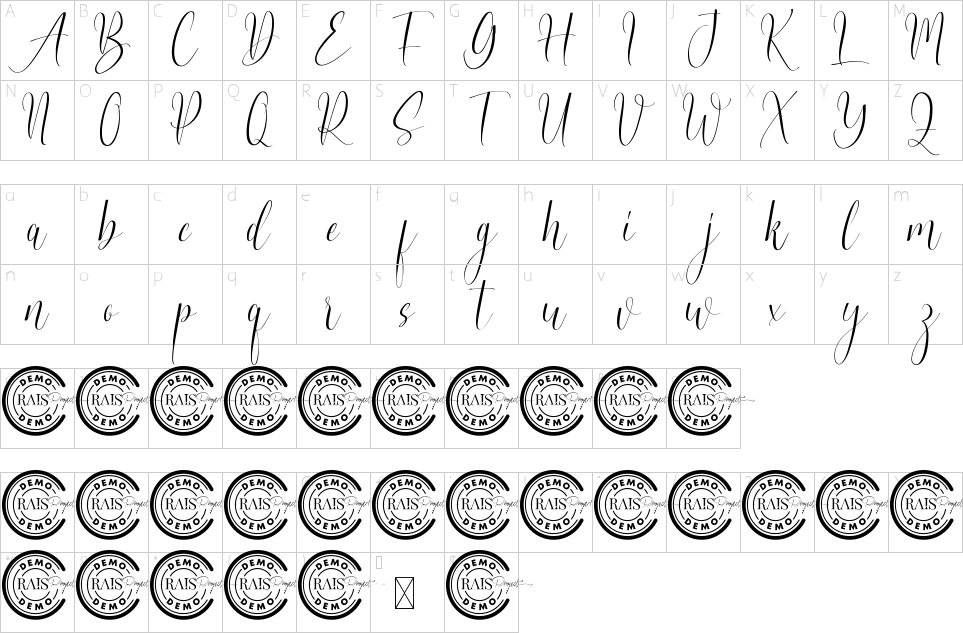
Descubra a beleza da fonte Melody Romantic, perfeita para expressar sentimentos leves e românticos em seus projetos. Desenvolvida pela RaisProject, essa elegante fonte é perfeita para quem busca uma mistura suave de delicadeza e romantismo em suas criações digitais. Melody Romantic não apenas proporciona uma escrita atraente e confortável para uso cotidiano, mas também oferece uma paleta de personalização que pode tornar qualquer design mais romântico e sedutor. Com seu design armonioso e detalhes cuidadosamente escolhidos, a fonte Melody Romantic é a escolha ideal para qualquer projeto onde um toque de romantismo é fundamental. Se você está procurando por uma fonte romanceada e gratuita, a fonte Melody Romantic é uma ótima opção para a sua necessidade.